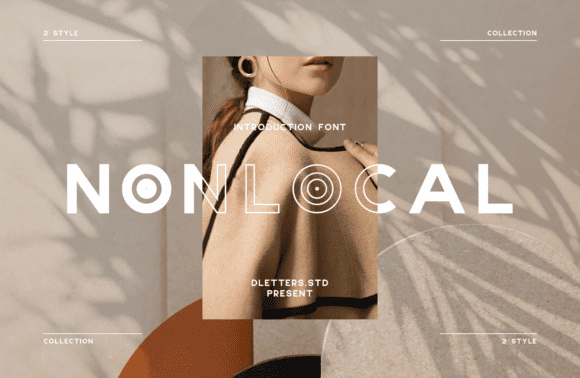
Название: Nonlocal Font (2021)
Nonlocal - это классный, современный и простой шрифт.
Независимо от темы, этот шрифт станет отличным дополнением к вашей библиотеке шрифтов, так как он способен приподнять любое творение.